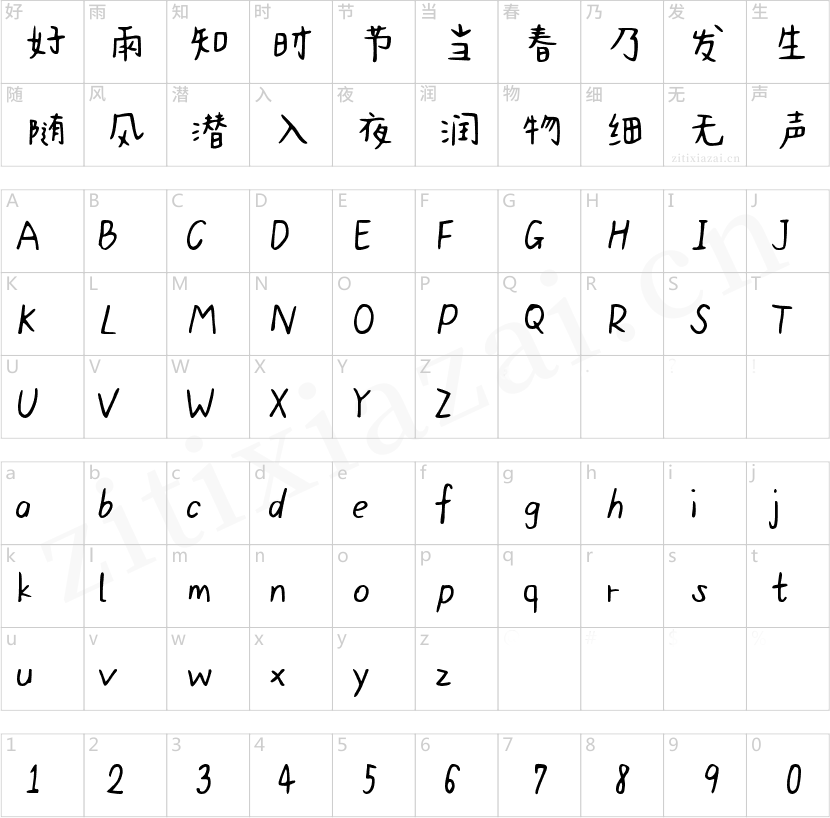
Aa做个俗人
Aa做个俗人,这款字体结构工整、笔画清晰,兼顾美观与易读性,适用于标题、正文、海报、包装、LOGO 等多种场景。字形优雅稳定,风格百搭耐看,适配日常排版与创意设计,让文字呈现更舒适、更具质感。Aa做个俗人一笔一画,皆是细节,以均衡的比例、流畅的线条打造舒适视觉体验,字形端正大气,风格简约现代。无论是商业设计、品牌宣传还是日常排版,都能轻松驾驭,让文字更有格调与力量。Aa做个俗人字体下载。
Aa做个俗人字体
Aa做个俗人是一款非常具有艺术性的字体,它的设计灵感来源于对古典艺术的研究,同时又融入了现代字体设计的元素。字形优美,笔画粗细变化自然,给人以大气、典雅的感觉。Aa做个俗人是一款既传统又现代的字体,它的设计充满艺术感,美观大方,实用性也非常强。无论是对于设计师还是对于普通读者来说,都是一种非常不错的字体选择。Aa做个俗人适合用于具有艺术感的场合,比如海报、宣传单张、书籍封面等。由于其字形流畅且具有动态感,也适合用于大量的文本排版,如报纸、杂志等。
Aa做个俗人详情